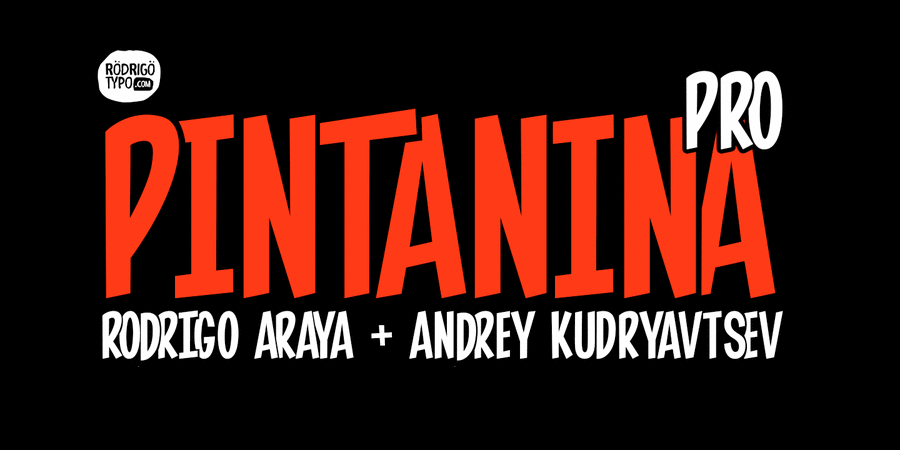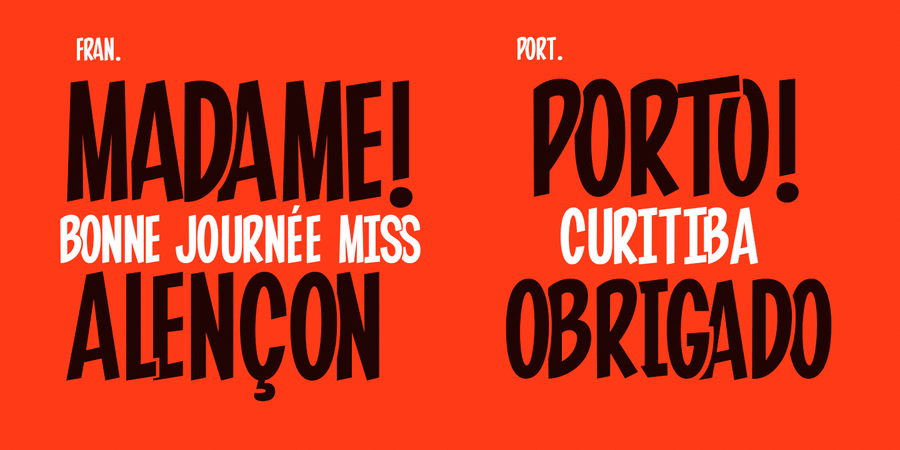
Pintanina Pro (2 шрифта)
Опис гарнітури Pintanina ProШрифт Pintanina був розроблений у 2013 році і мав багато альтернативних символів у якості лігатур. Це дуже вузький шрифт для заголовків, заснований на коміксах Кондоріто. Згодом Pintanina була ретельно дороблена, а також додана кирилиця і грецька абетка.
Шрифт розробили Родріго Арая Салас за участю Андрія Кудрявцева у 2015 році.
Особливості сімейства шрифтів Pintanina ProХіт десятиліття:
стінгазета, журнал, комікс, пакування, листівка, анімація, мультфільм, вивіска, обкладинка, плакат, реклама, етикетка, афіша, меню, цінник, відео, оголошення, стікер, наліпка, титри Адаптованість гарнітури до носіїв:
Асоціації з сімейством шрифтів Pintanina ProОсобистість і характер гарнітури:
виразний, потішний, високий, іронічний, здоровий, бадьорий, характерний, гулящий, дозвільний, пещений, гладенький, цікавий, студентськиий, тусовочний, прикольний, динамічний, живий, непосидючий, неформальний, молодіжний, яскравий, веселий, задерикуватий, смішний, радісний, грайливий, пустотливий, рухливий, оригінальний, свіжий, помітний, дитячий, карикатурний, мультяшний, дотепний, щасливий, святковий, творчий, дзвінкий, чистий, твердий, позитивний, вільний, мотивуючий, сміливий, гучний, гострий, артистичний, активний, значний, тісний, впевнений, сильний, стійкий, революційний, важливий, робочий, амбітний, гордий, різкий, вуличний, кричущий, Простий, елементарний, пухкий, товстий
фаст фуд, крамниця, графіті, пригоди, розваги, вечірка, торгівля, реклама, магазин, гра, дитяча книжка, табір, гумор, анімація, їжа, закуска, відпочинок, цирк, мультфільм, шоу, кіно, свято, атракціон, піцца, мітинг, революція, відео, страйк, Протест, супергерой, дискотека, аквадискотека, графіка, ілюстрація, ранок, прапор, кінотеатр, меню, іграшка Гарнітура асоціюється з віком: